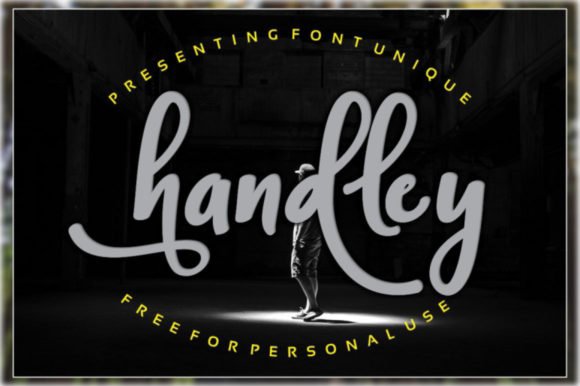
Handley Font
Handley Font – خط أنيق وعصري لمشاريعك الإبداعية
Handley Font هو خط مميز يجمع بين الأناقة والبساطة، مما يجعله خيارًا مثاليًا للمصممين وروّاد الأعمال الذين يبحثون عن لمسة احترافية لمشاريعهم. يتميز بتصميمه الأنيق وسهولة قراءته، مما يجعله مناسبًا للاستخدام في الشعارات، التصاميم الطباعية، الإعلانات، مواقع الويب، والمطبوعات المختلفة.
مميزات Handley Font:
✔️ تصميم عصري وجذاب
✔️ مثالي للشعارات والتصاميم الطباعية
✔️ دعم كامل لأحرف كبيرة وصغيرة
✔️ سهل الدمج مع أنماط التصميم المختلفة